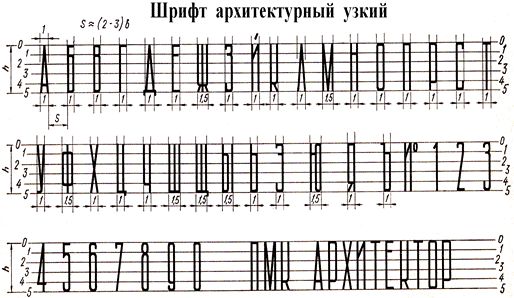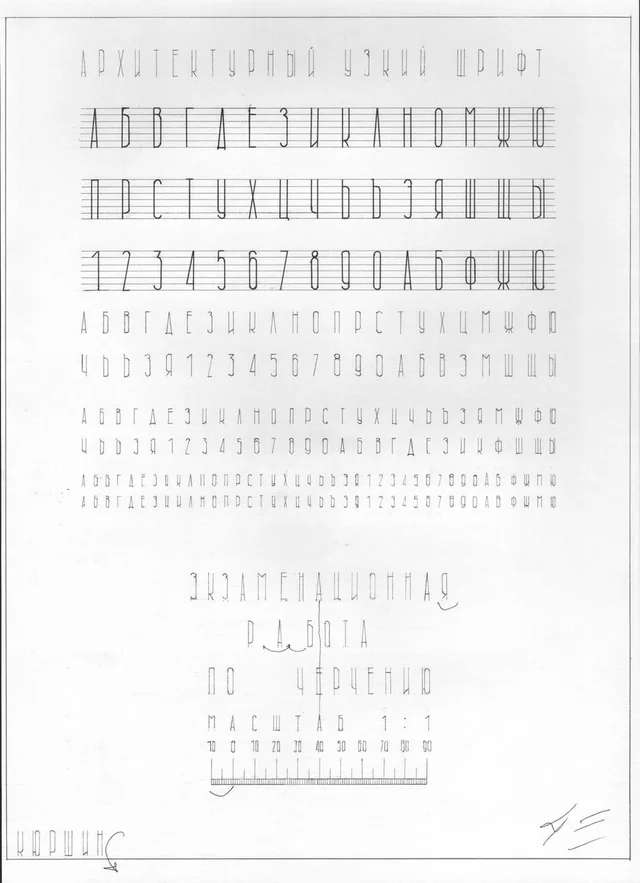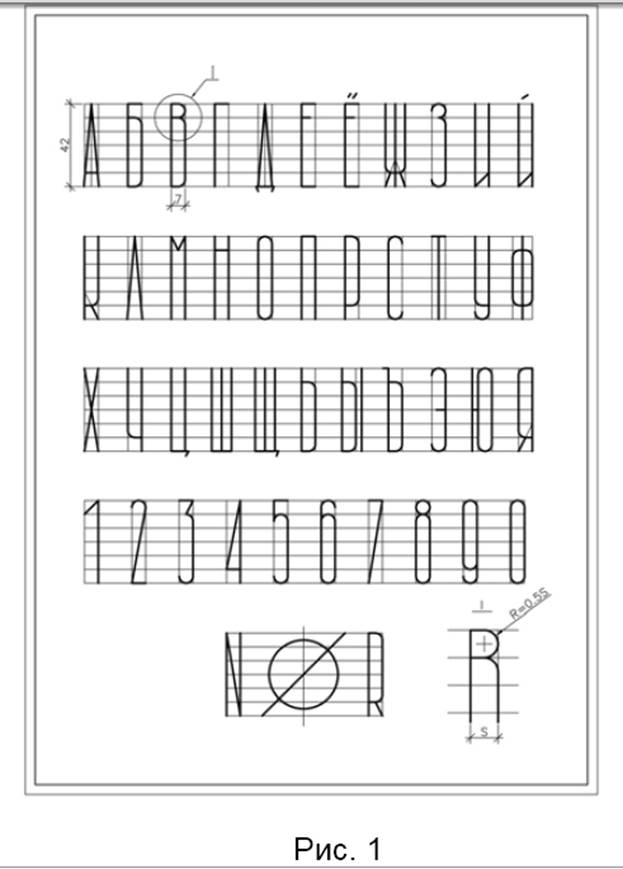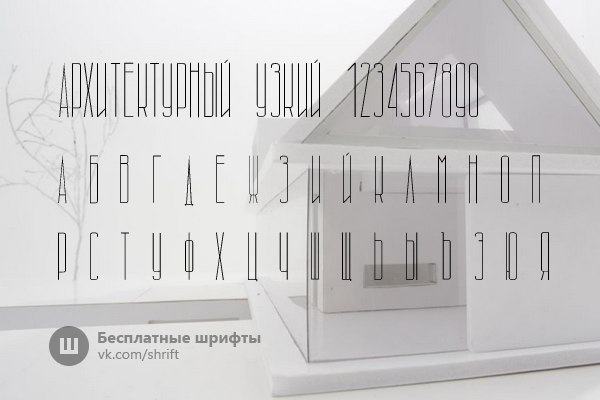
В этом случае ширина их для данного размера h берется по ближайшему меньшему размеру шрифта. Например, ширина буквы А для шрифта 10 может быть взята 5 мм вместо нормальной 7 мм. Форма более узких букв и цифр должна быть сохранена. [31]
Перед изучением начертания букв необходимо знать рациональные приемы нанесения вспомогательной сетки. Для разметки ширины букв и промежутков между ними рекомендуется применять полоски бумаги, на которых указаны нужные размеры, или трафареты с прорезями для букв в виде параллелограммов. При выполнении сетки лист должен быть закреплен, а при исполнении надписей его рекомендуется открепить, так как писать наклонным стандартным шрифтом значительно удобнее, если лист положен с небольшим наклоном ( – 25) к горизонтальной линии. [32]
Ширина буквы вместе с расстоянием между буквами должна примерно равняться высоте буквы, а у широких букв ( Д, Ж, Ф, Ш, Щ, Ы, Ю) на расстояние больше.
Наименование чертежа должно быть расположено симметрич-но по длине и высоте. Расстояние между словами должно быть не менее ширины буквы текста. Размер этот обычно берется в соответствии с полученным размером длины слов в тексте. [34]
Горизонтальный элемент буквы А проводят на расстоянии 2 / й от основания строки. Вершина этой буквы находится в точке деления ширины буквы пополам. [35]
| Архитектурный узкий шрифт. [36] |
Расстояния между словами и числами AI должно быть не менее ширины букв текста. [37]
Высоту букв и цифр принимают равной 2, 3, 4, 6, 8 и 10 мм, что и определяет размер шрифта. Ширину нормальных букв принимают примерно в 2 / 3 высоты, ширина широких букв
( Д, Ж, М, Ф, Ш, Щ, Ы, Ю) равна примерно их высоте.
Толщина обводки букв и цифр составляет 1 / 20 высоты.
[38]Не последнюю роль в реализации рекламной идеи выполняет шрифт. Используемые в рекламе шрифты отличаются начертанием буквенных знаков, соотношением высоты и ширины букв и толщиной штриха. [39]
Промежуточное положение занимают буквы А и М, ширина 62 которых равна 5 / 7 / i для основного и 6 / 7й – для широкого шрифтов. Ширина Ья цифры I равна 2 / 7ft – Например, для шрифта размера 10 ширина буквы Б равна для основного шрифта 5 7 мм, а для широкого – 7 мм. Ширина буквы Ж соответственно составляет 8 6 и 10 мм, а буквы М – 7 и 8 6 мм. Ширина цифры 1 для шрифта размера 10 равна 2 9 мм. [40]
Допустимые смещения знаков по вертикали составляют 1 7 мм или 0 5 размера буквы шрифта. Растры запускаются периодически, частота их запуска подбирается так, чтобы на расстояние, равное
Один эм равен 18 единицам. Единицы используются при расчете разрядки ( spacing-in ( spacing-out)) в соответствии с длиной строки и шириной букв. [42]
Командная длина – это команда, значением которой является длина. Можно использовать также относительные единицы измерения длины ех и em: они зависят от размера текущего шрифта и равны примерно высоте буквы х и ширине буквы М, соответственно. [43]
На рис. 94 показан второй ряд прописных букв, состоящих также из прямолинейных элементов. Ширина букв этого ряда отличается от ширины букв первого ряда. [44]
Промежуточное положение занимают буквы А и М, ширина 62 которых равна 5 / 7 / i для основного и 6 / 7й – для широкого шрифтов.
Ширина Ья цифры I равна 2 / 7ft – Например, для шрифта размера 10 ширина буквы Б равна для основного шрифта 5 7 мм, а для широкого – 7 мм. Ширина буквы Ж соответственно составляет 8 6 и 10 мм, а буквы М – 7 и 8 6 мм. Ширина цифры 1 для шрифта размера 10 равна 2 9 мм.
Шрифтовые композиции
Шрифтовые композиции.
Шрифтовые композиции постоянно используются в дизайне окружающей среды. Это – памятные доски, вывески, надписи на упаковках и этикетках промышленных товаров и т.д. Надписи имеют не только информационное значение, но и создают эстетическое качество среды обитания человека.
В зависимости от назначения, шрифт может быть изящным или массивным, строгим или живописным.
Главными эстетическими критериями выбора того или иного шрифта является гармоничность его пропорций, красота рисунка каждой буквы, простота и понятность, четкость и соразмерность. В шрифте все буквы должны гармонично сочетаться друг с другом в любых возможных комбинациях, быть красивыми и хорошо читаемыми.
Еще на заре своего развития человек стремился зафиксировать и передать определенную информацию с помощью шрифта, отразить исторические события и свое отношение к ним. Это послужило причиной появления предметного и картинного письма. Постепенно, для ускорения процесса письма, появились знаки-символы. Такой вид письма называется образно-символическим.